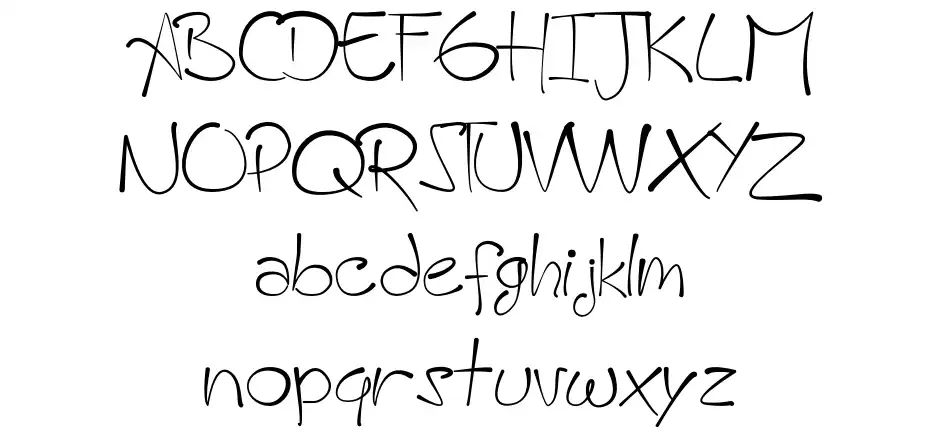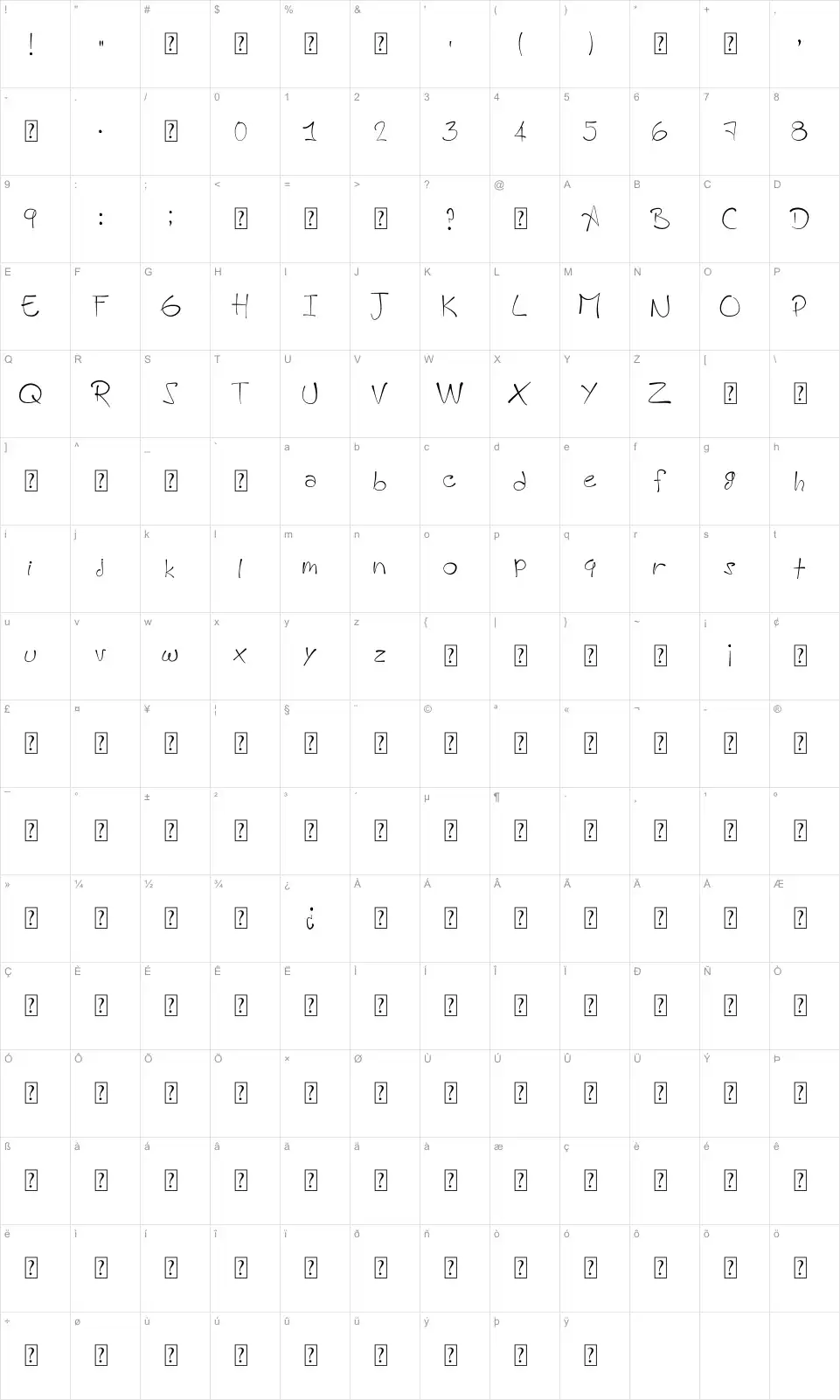
A fonte ‘A HandMade Font’, criada pelo designer Gastón Jacquier, é uma elegante opção para quem busca um estilo elegante e retrô. Se você está à procura desta fonte, não hesite em baixá-la ou gerar uma pré-visualização personalizada de texto para vê-la antes de começar a usá-la. Formada na categoria de Script e com um estilo handwritten, A HandMade Font é uma delícia para trabalhos pessoais e projetos que valorizam um touch de escrita artesanal. Com uma licença gratuita para uso pessoal, formato OTF e tamanho de arquivo de 457 KB, esta fonte é uma ótima opção para quem busca uma opção de fontes de alta qualidade sem custos. Adicionada à nossa base de dados em 12 de julho de 2022, esta fonte já recebeu 1738 downloads, demonstrando o seu valor e popularidade. Seja para criar uma identidade visual única ou para adicionar um toque personalizado a seus projetos, esta font é uma excelente escolha.
Categoria: Script › Handwritten
Designer: Gastón Jacquier